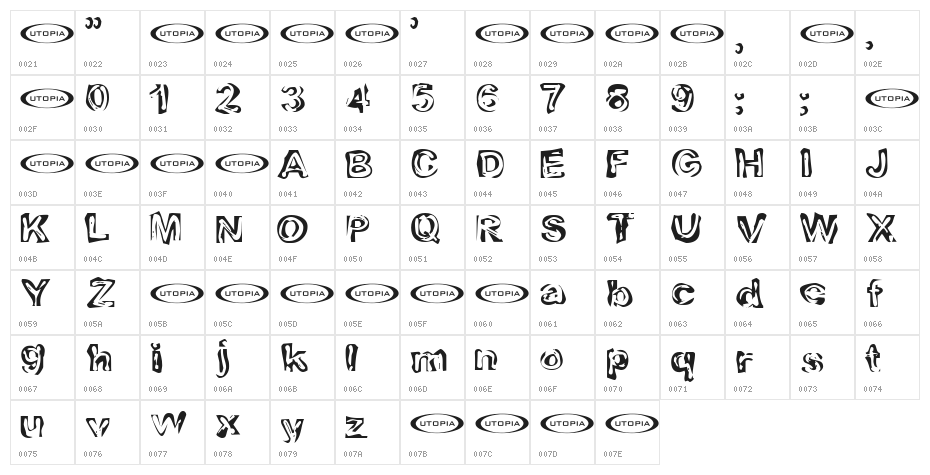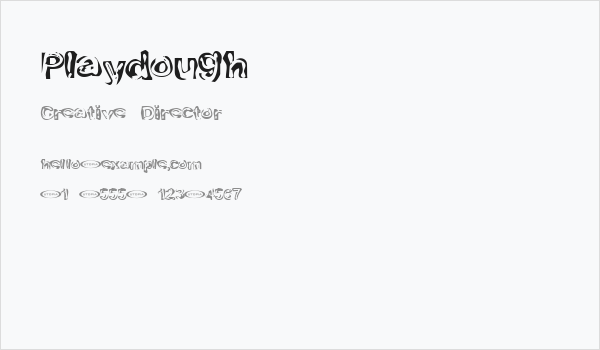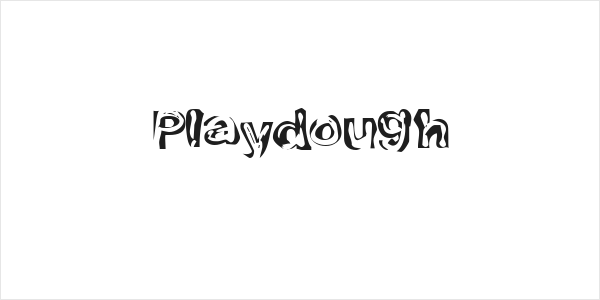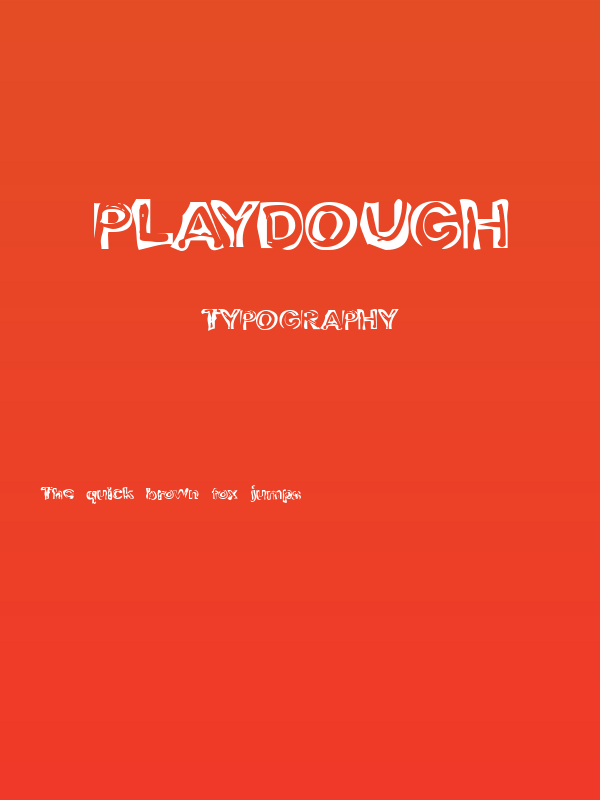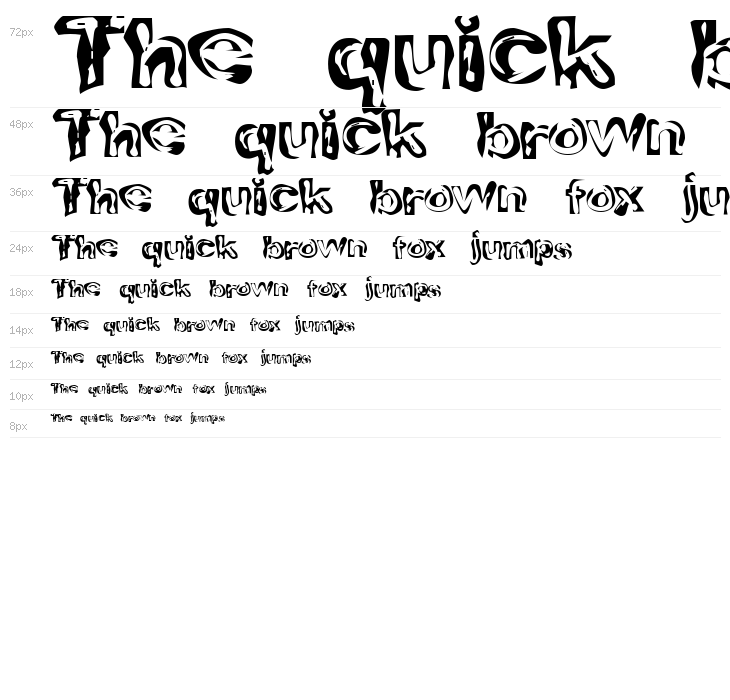
Playdough Font
| समग्र शैली | Playful, Creative |
| उपयोग का मामला | Headlines, Logos, Posters |
| सुझाए गए प्रोजेक्ट | Ideal for children's books, playful branding, creative posters, and any project seeking a fun, informal touch. |